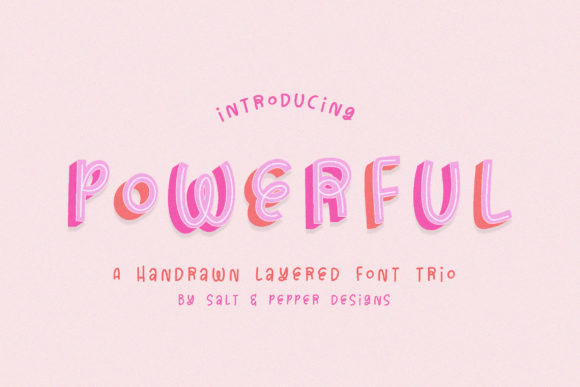
Powerful Trio
Trouver les bons éléments de conception peut être un défi, mais Powerful Trio propose une collection exceptionnelle qui rehausse instantanément votre travail.
Que vous créiez des produits POD (impression à la demande), des invitations de mariage ou des visuels pour les réseaux sociaux, Powerful Trio est un choix idéal.